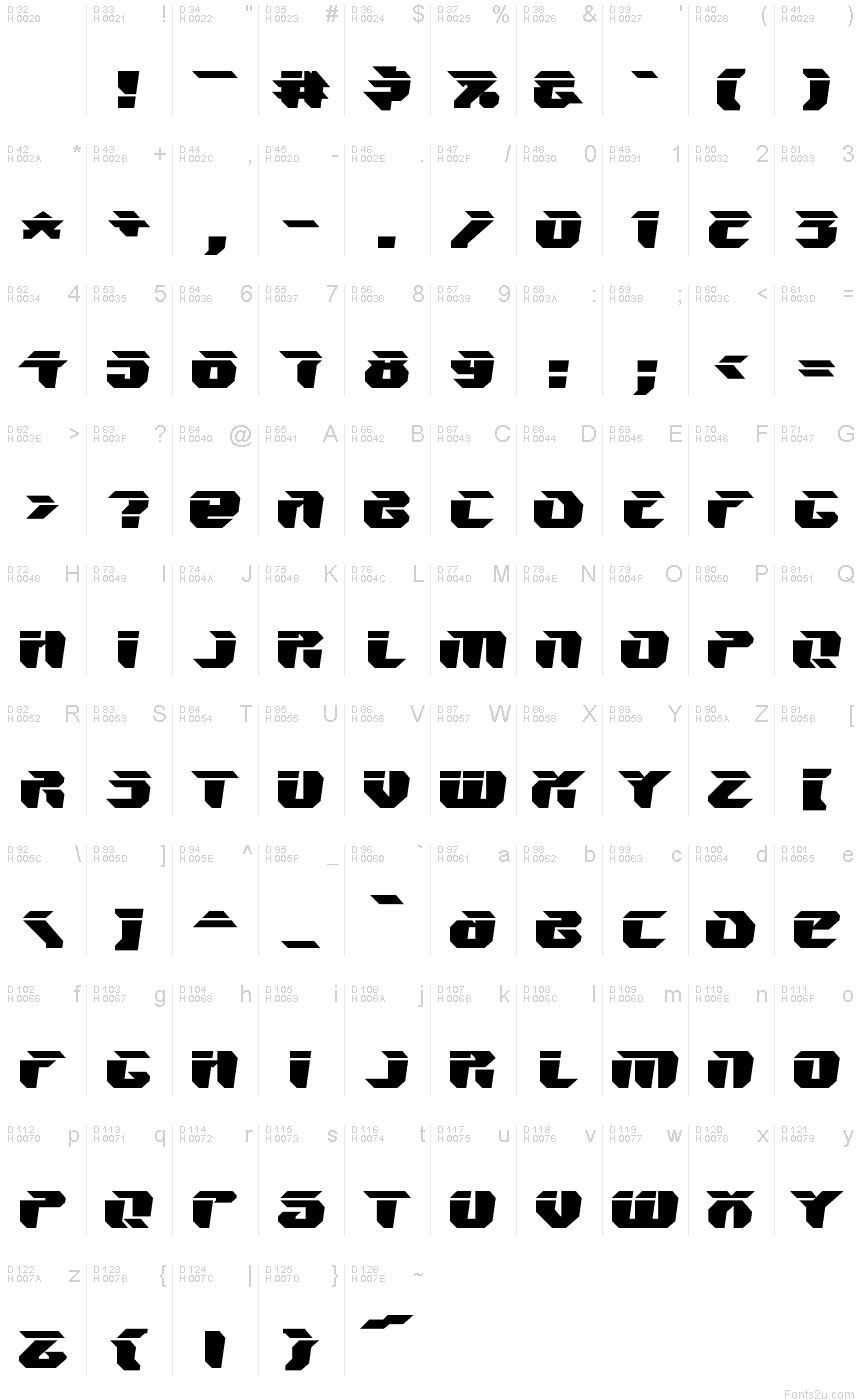
V5 Ampon Warped, die kostenlose, futuristische Techno-Display-Schrift von Roberto Christen, bringt kantige, maschinell geformte Buchstaben mit tiefen Schnitten und angeschrägten Ecken – ein Look wie aus alter Arcade-Hardware oder Cyber-Grafiken der späten 90er. Die Buchstaben sind breit, blockartig und durch wiederkehrende horizontale Schnitte eng miteinander verzahnt, sodass die gesamte Schrift wie ein einziger, eckiger Bewegungsstrom wirkt.
Sie eignet sich ideal für Plakatüberschriften, Game-Branding, Mixtape-Cover, Titelkarten und Nachtclub-Flyer, wenn eine kostenlose Schrift einen synthetischen, energiegeladenen Sound braucht, ohne ins generische Sci-Fi-Klischee abzurutschen. Da die Formen so aggressiv ineinandergreifen, funktioniert sie auch hervorragend für kurze Logos, Monogramme und Cover-Texte, die von diesem verschweißten, industriellen Rhythmus profitieren.